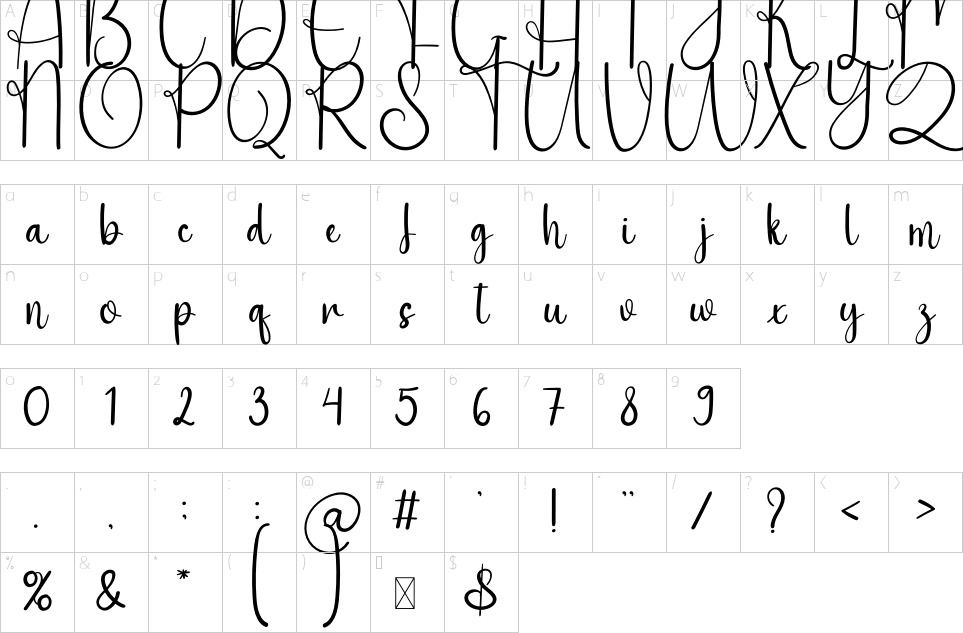
Aproveite a oportunidade de adquirir uma nova e única fonte para seu projeto em português brasileiro com a Daddy Smile Font. Desenvolvida por William Jhordy, esta elegante família de fontes oferece uma aparência suave e encantadora que irá dar um toque especial às suas criações. Com 1,105 downloads desde sua disponibilização, sabemos que os fãs da estética brasileira encontraram nesta fonte algo de muito especial. A Daddy Smile não apenas destaca seu uso em projetos visuais, mas também oferece uma paleta de caracteres únicos e personalizáveis que podem complementar qualquer projeto de design gráfico. Se você está procurando por uma nova adição para seus designs ou até mesmo um novo estilo para suas criações digitais, a Daddy Smile pode ser perfeita para você. Descubra por si mesmo o poder desta fonte única e inovadora!